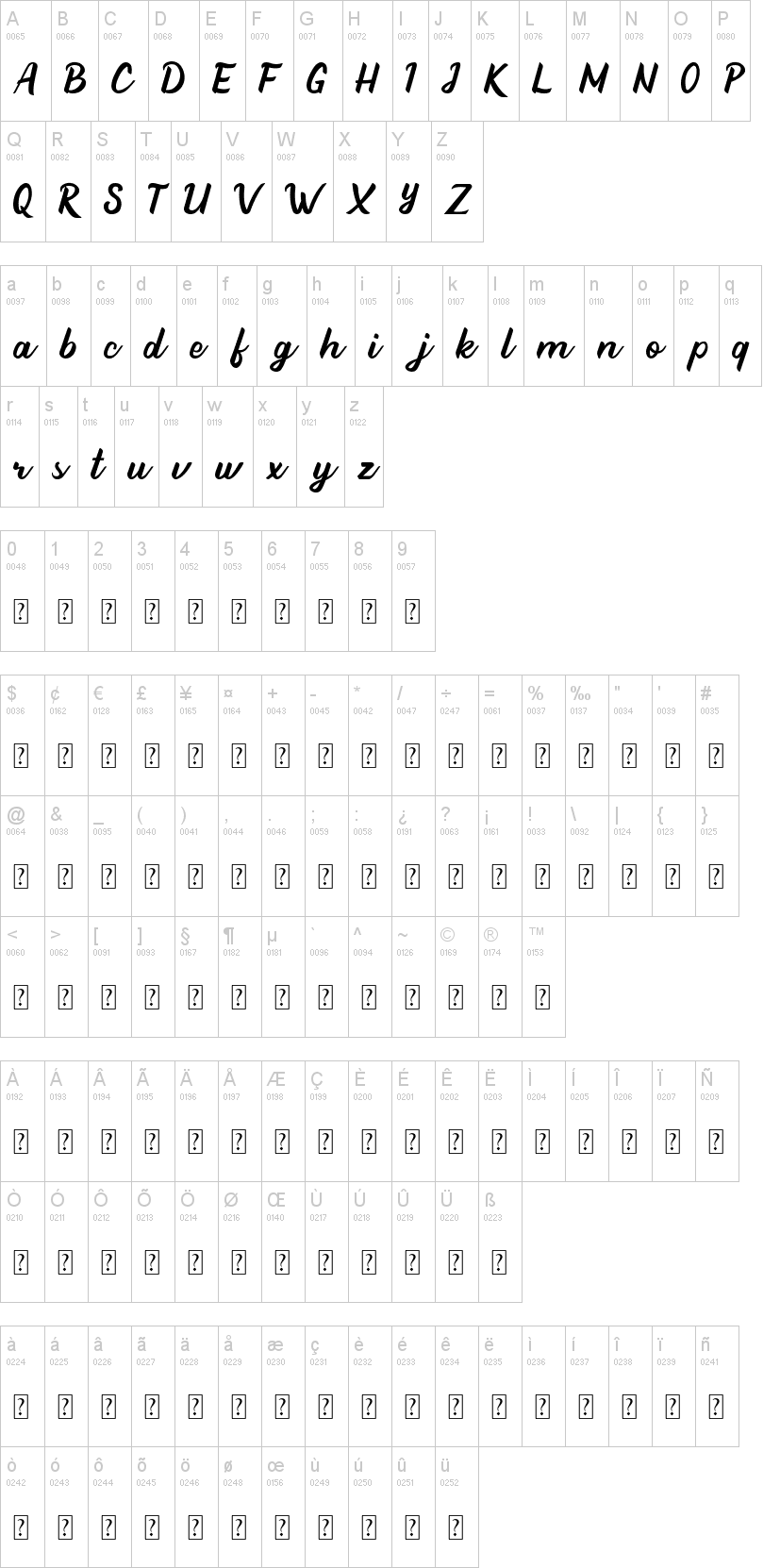
? Beathy 字体是一款简洁、优雅、现代的英文字体,它的字体结构让您的文字看起来更加清晰、简洁。它可以用于任何类型的设计,从标题到段落,甚至是网页设计,都能够让文字更加美观。它的字体特点是拥有高度细节和自然的节奏,可以让您的文字更加清晰、简洁。内容介绍
Beathy是一款非常不错的手写艺术字体,具有很好的视觉感,适合于文化类的宣传设计、商业类品牌的广告和产品包装设计以及个性化文字排版等较多场景。